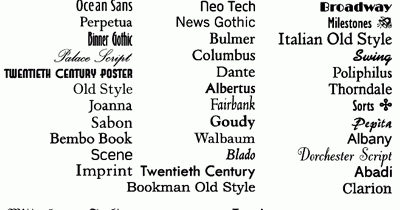
Tipografia
La tipografía es el fiel reflejo de una época.
Tipografia
Es el conjunto de características visuales de las letras y números de un texto, tales como su diseño, su forma y su tamaño.
Estructura de la letra
Es esa señal o marca que se imprime, transfiere, pinta o esculpe y viene a ser la unidad fundamental del lenguaje escrito
puede presentarse en:
Capitales
Minúsculas
Números
Versalitas
Ligaduras
Símbolos
Partes de la letra
Asta
Astas montantes
Anillo
Brazo
Cola
Ascendente
Descendente
Oreja
Ojo
Rebaba
Gracia
Clasificacion Tipografica
Hay cinco elementos que nos sirven para clasificar a las familias tipográficas:
*La presencia o ausencia del serif o remate
*La forma del serif
*La relación curva o recta entre bastones y serifs
*La uniformidad o variabilidad del grosor del trazo
*La dirección del eje de engrosamiento
Tiene dos grandes grupos fundamental
-Romanas Antiguas
-Romanas de Transición
-Romanas Modernas
Egipcias
Tipos de Patines
Mixtiforme
Filiforme
Rectiforme
Cuadrangular
La forma de alinear éste puede ser
Alineado
Izquierda
Derecha
Centrado